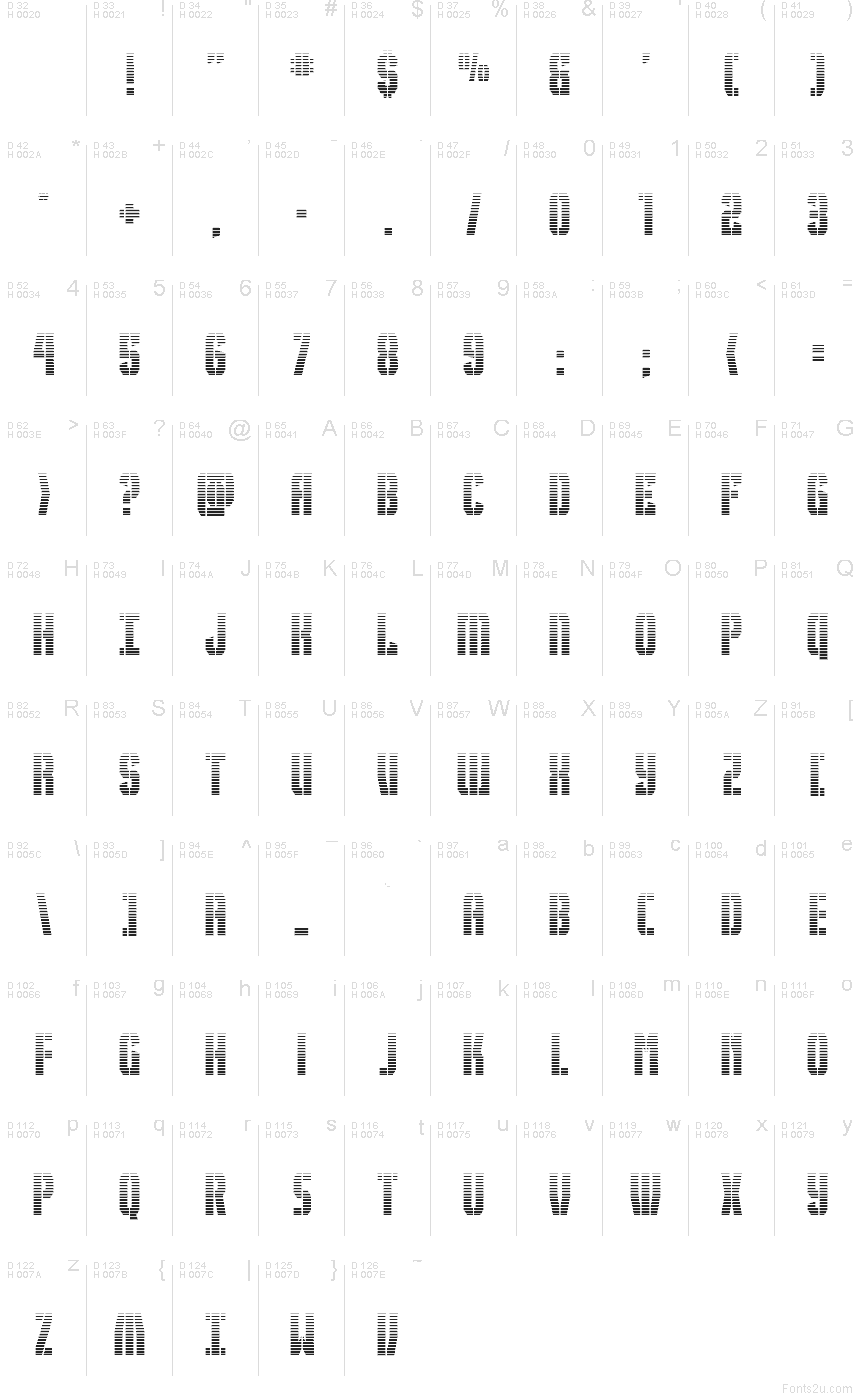
Gorilla Warfare Gradient de Iconian Fonts es una tipografía display gratuita de estilo militar, construida a base de franjas horizontales densas que le dan a las mayúsculas un toque de interferencia televisiva y estética de barricada. Las letras parecen cortadas específicamente para pósteres de acción en lugar de titulares convencionales; sus siluetas anchas, interrumpidas por rayas repetitivas, logran un diseño potente y un estilo táctico inconfundible.
Encaja perfectamente en gráficos de streetwear, títulos de videojuegos, titulares de pósteres, branding de e-sports y portadas de álbumes donde importa más una estética de combate cruda que el pulido tradicional. Al ser una fuente gratuita, también funciona muy bien para eslóganes cortos, nombres de facciones y monogramas, ya que las franjas superpuestas aportan suficiente impacto visual para sustentar el diseño incluso con pocas letras.